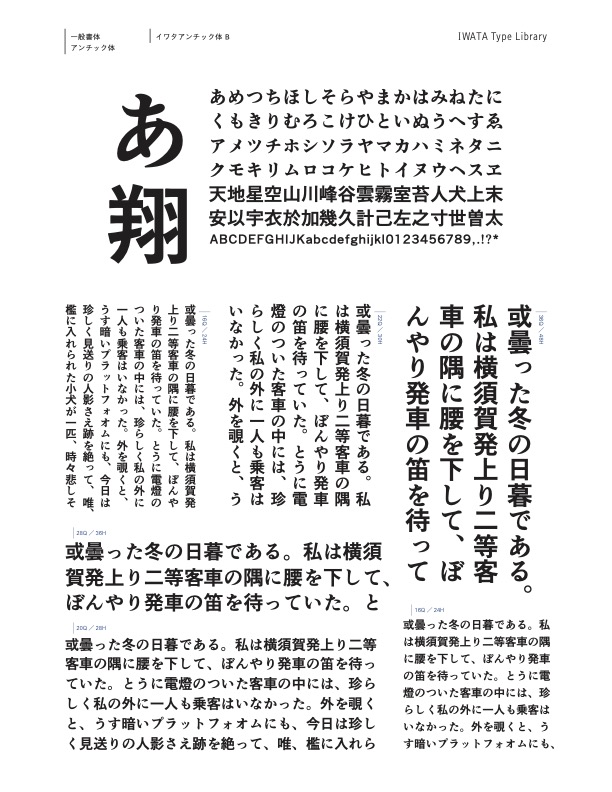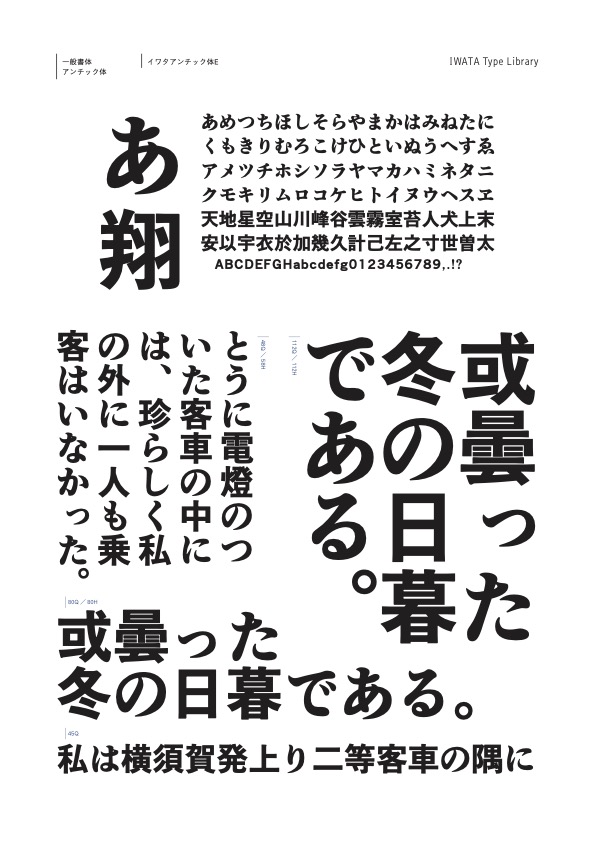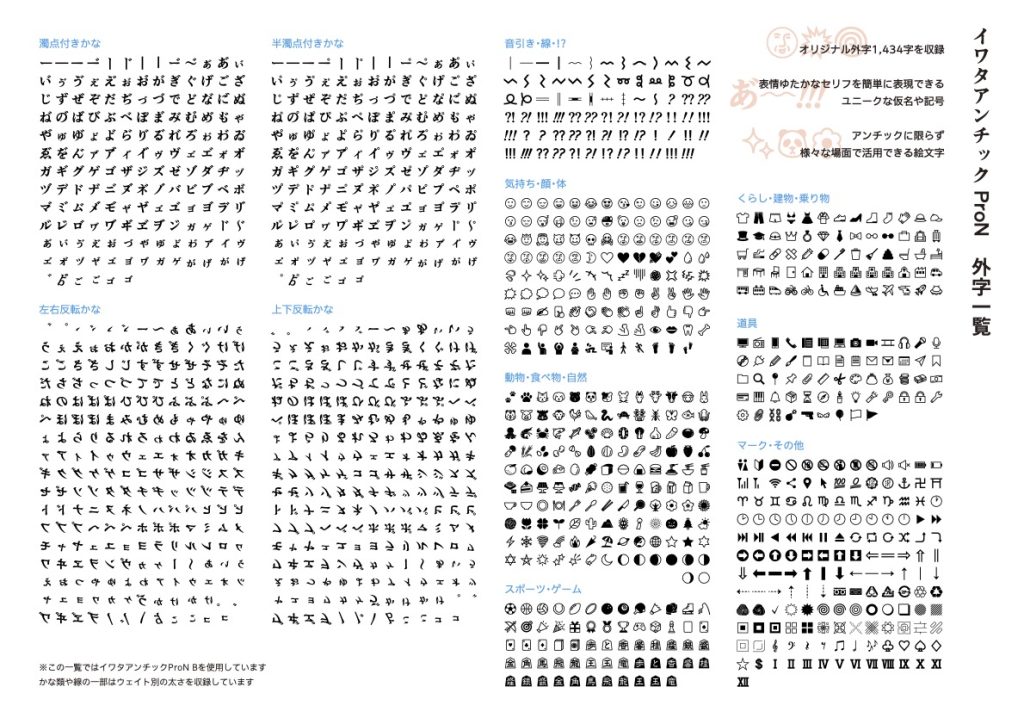
力強いゴシック体の漢字と筆書き風の柔らかいアンチックのかなを組み合わせた書体です。
その表情豊かなデザインは、漫画の吹き出しや辞書の見出しなどに広く使用されてきました。
コミックや同人誌はもちろん、映像などのエンターテインメント分野にも適しており、親しみやすく読みやすい書体として活用されています。
OpenType版には、従来の外字セットに新たな絵文字を追加しています。